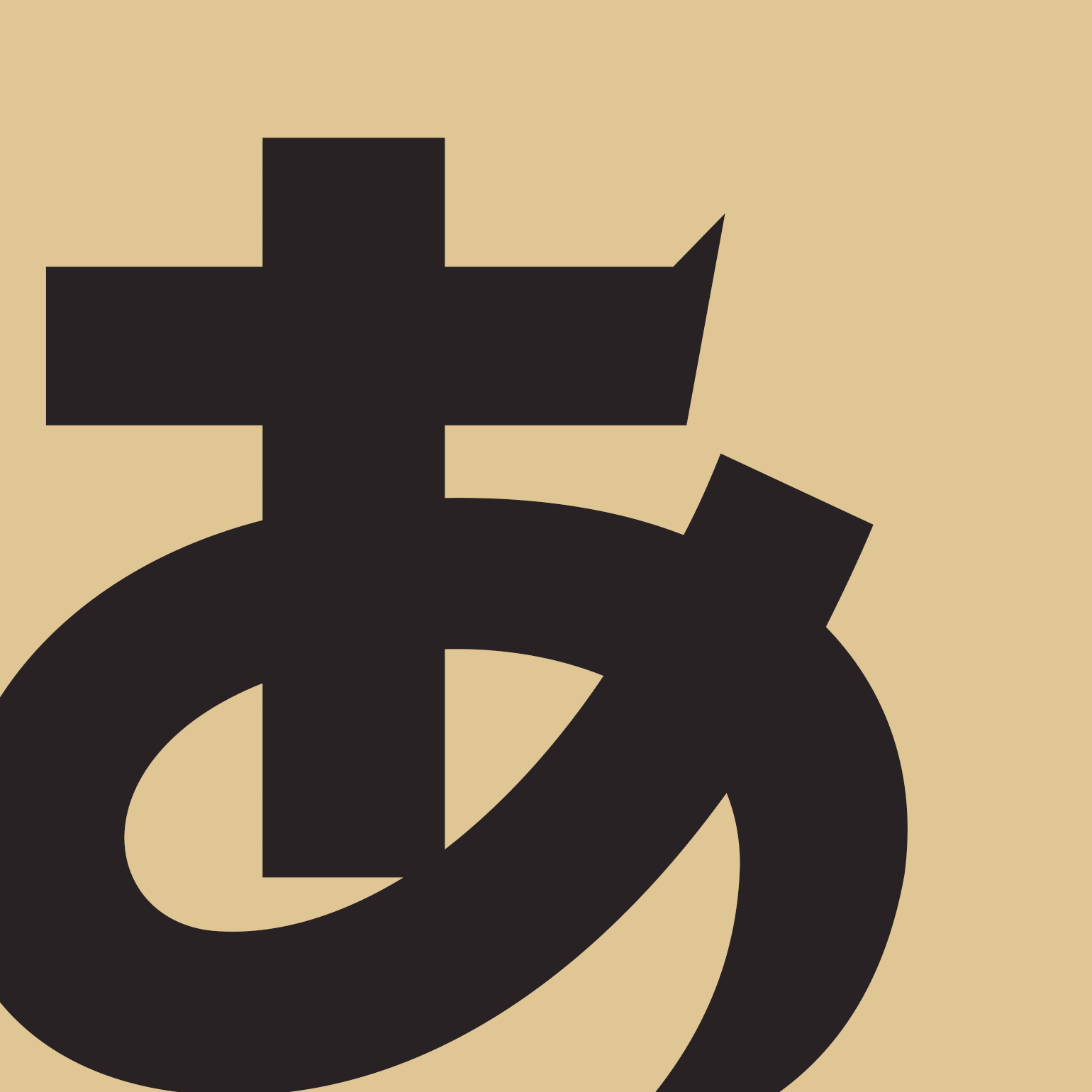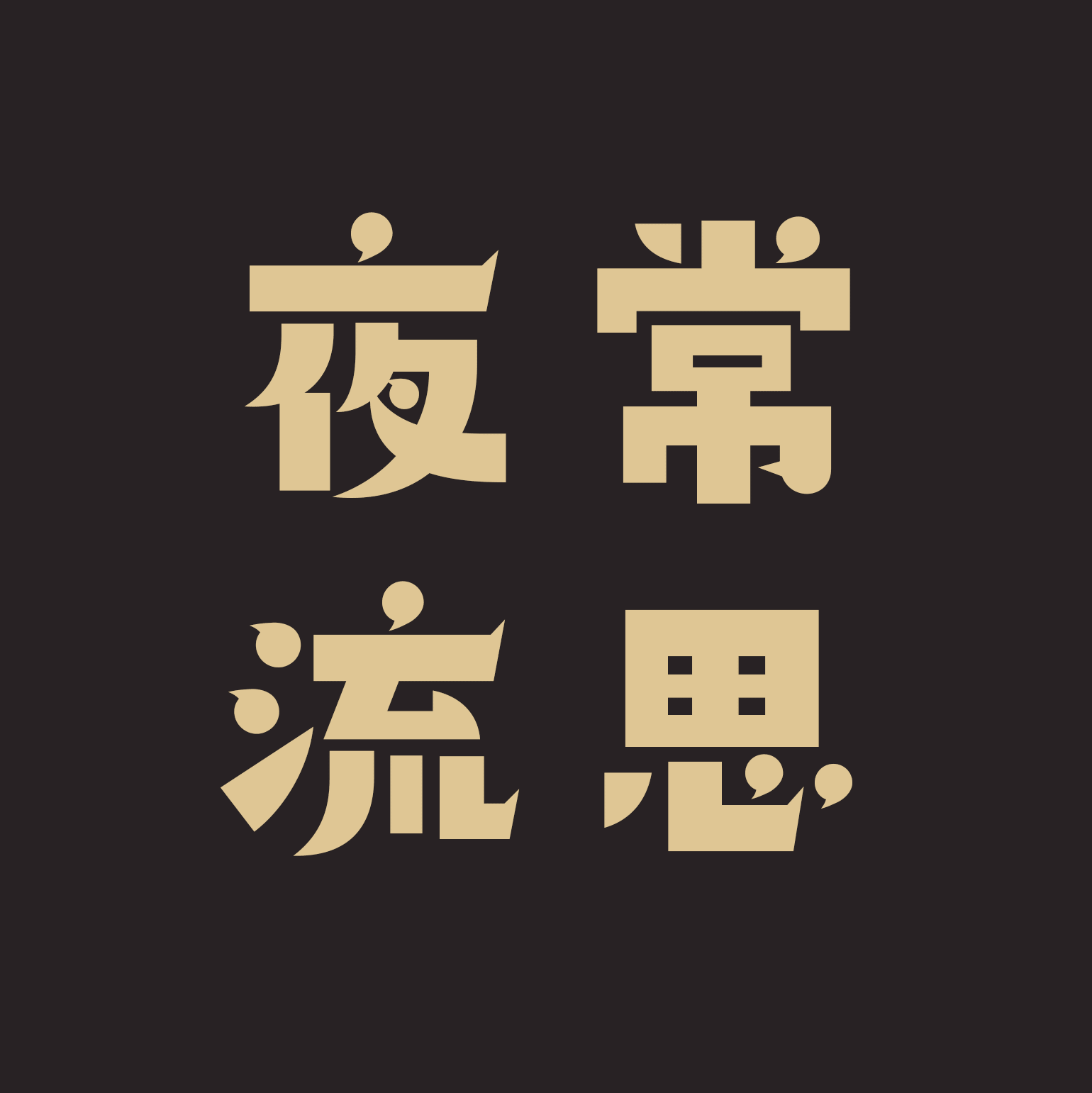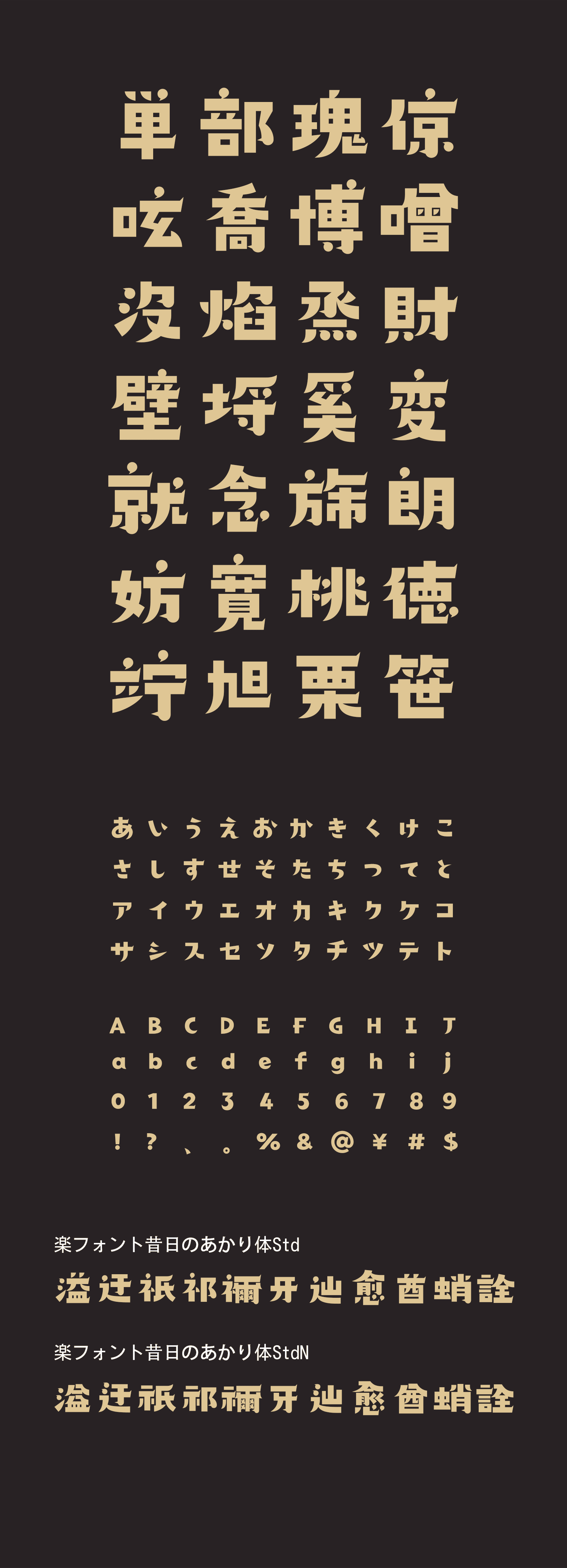
昔日のあかり体(せきじつのあかりたい)
楽フォント
昔日のあかり体(せきじつのあかりたい)
丸みのある形とノスタルジックな筆致が生み出す、あ
たたかくやさしい雰囲気のフォントです。ふくらみの
ある文字面で読みやすく、親しみやすさも魅力です。
文芸系タイトルや物語表現、やさしい世界観のブラン
ド制作に最適です。